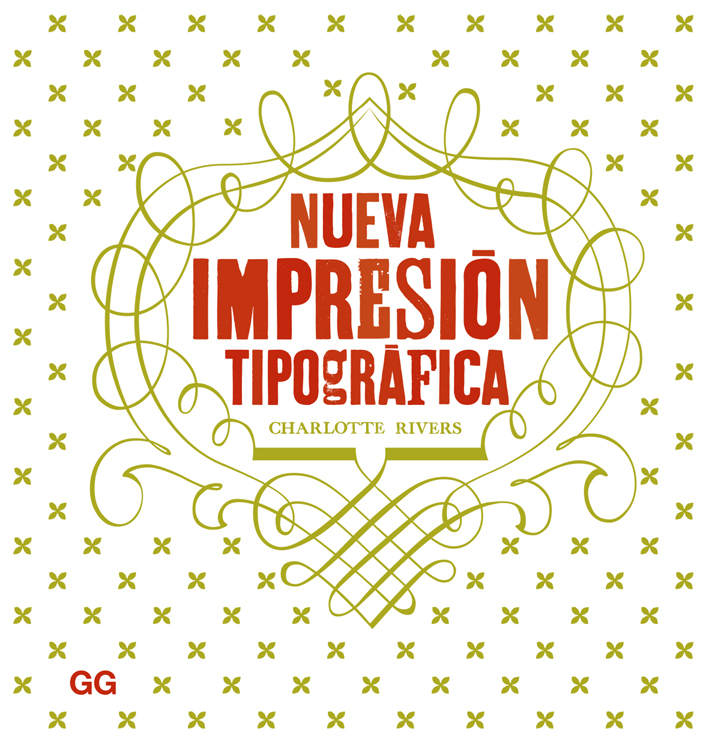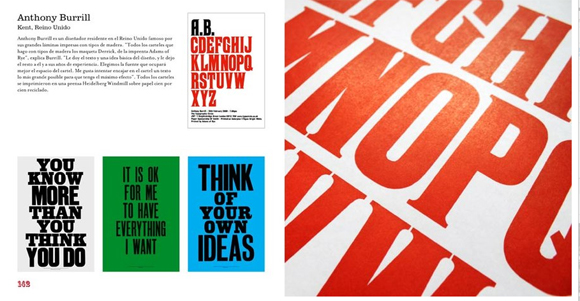
La imprenta tradicional con tipos de plomo y de madera está de moda. No hay nada más que fijarse en la cantidad de estudios tipográficos que surgen como setas en todo el mundo. Y las editoriales sobre diseño también muestran su interés por documentar y difundir esta «resurección de la imprenta». Gustavo Gili acaba de poner en el mercado Nueva impresión tipográfica, un libro, realizado por la escritora Charlotte Rivers, que nos propone un repaso de lo que se está haciendo ahora mismo en impresión tipográfica.
El libro tiene varias virtudes: la primera de ellas es poner nombre a pequeñas imprentas e impresores que trabajan esta forma de comunicación artesanal, la segunda mostrar en sus páginas la versatilidad de está técnica y la tercera servir de inspiración para reciclar criticamente sus productos típicos ayudando a constituirla un método de expresión totalmente contemporáneo.
Y es que la impresión tipográfica nos devuelve algo que el ordenador nos había hurtado. La sensación táctil del diseño, el diseño que se puede tocar y que convierte una hoja impresa en un objeto tridimensional añadiendo una cualidad extra al propio objetivo formal de la comunicación. Y Nueva impresión tipográfica sin duda aporta con sus imágenes el punto ideal al debate entre tecnología y artesania en el mundo del diseño gráfico.